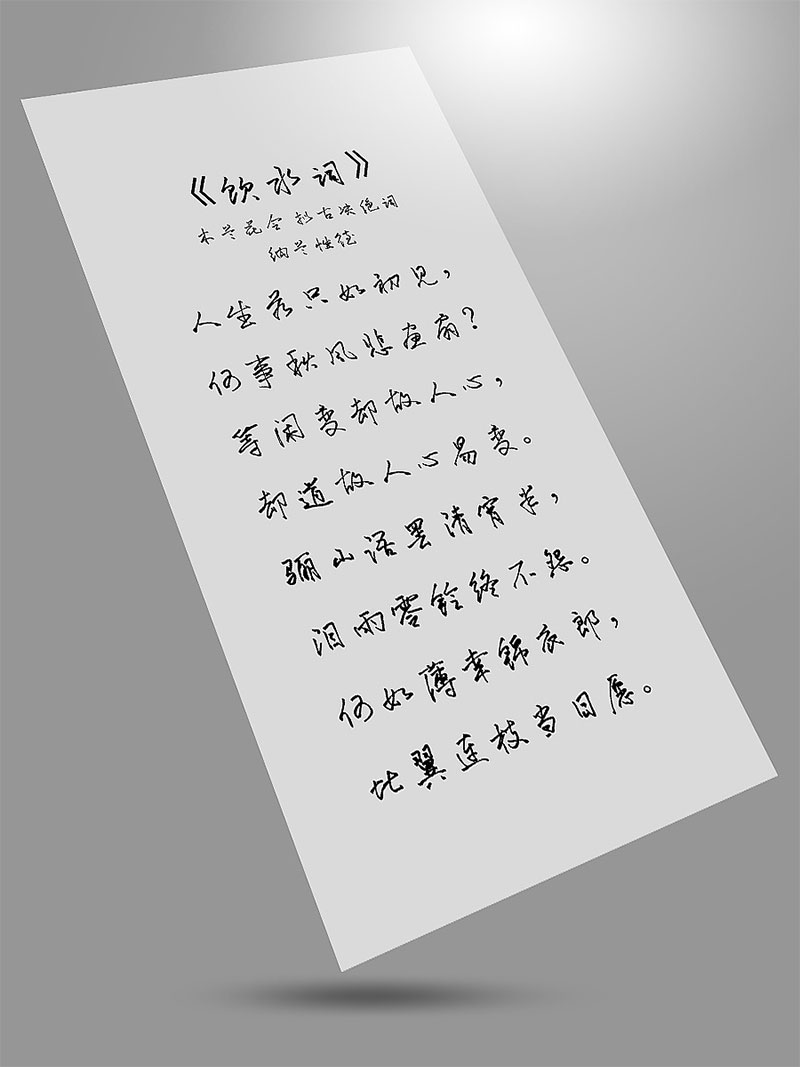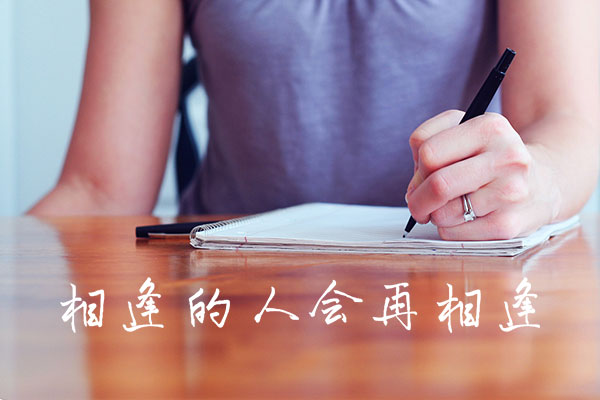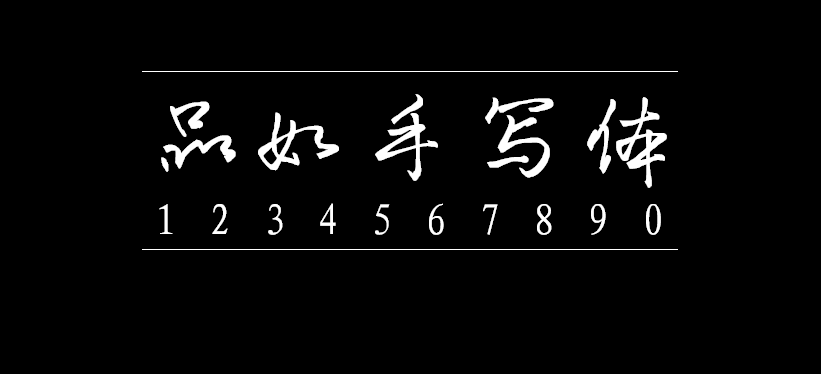
品如手写体
作者林芳柽,品如设计创意总监 淘宝装修市场专属讲师。曾任职于国际知名4A广告公司奥美,服务过奔驰、三菱、网龙、中国移动等知名客户。受阿里巴巴邀请参与撰写智库新书《全网诚信通》。 这些年下来,许多字体都开始收版权费,十分苦恼!作者自己是个书法爱好者,索性写一套自己的字库,想到就去做了。然后,历时半年时间,利用业余时间,写了这套字库。名字叫做【品如手写体】作者郑重承诺,永久免费可商用!!
品如手写体